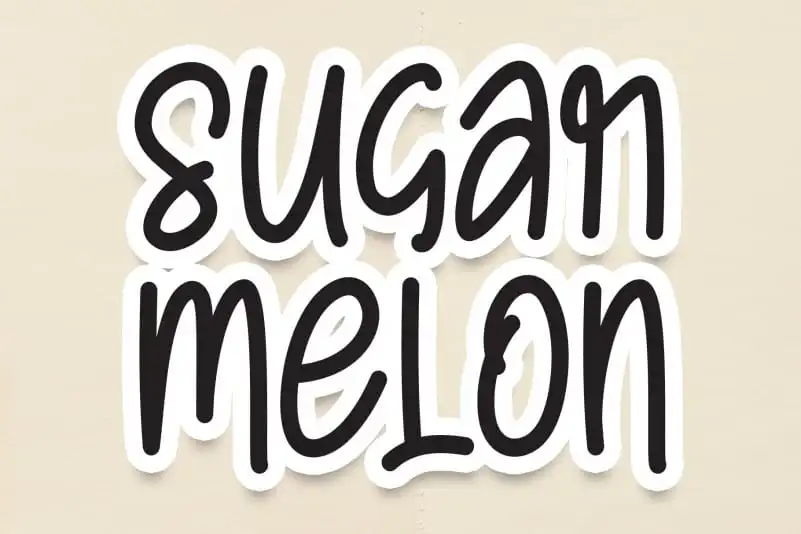
Sugar Melon Display Font – Download Grátis
A Sugar Melon Display Font é uma nova adição à coleção de caracteres digitais da creativeletter, apresentando-se como uma mistura única entre elegância e naturalidade. Este tipo de escrita é perfeito para designers que buscam um toque de criatividade na sua criação, trazendo profundidade e originalidade ao design. Embora seja classificado como um fonte de escrita feita à mão, a Sugar Melon Display Font não se limita apenas a esses limitados requisitos. Seu caráter fluido e expressivo permite que você explore uma variedade de estilos, desde letras delicadas até designs mais elaborados e chamativos. Este tipo é especialmente adequado para o uso em logotipos, selos, cabeçalhos ou qualquer outro elemento visual que deseje destacar sua personalidade e singularidade. Com um design cuidadosamente pensado, a Sugar Melon Display Font se torna uma fonte de escolha perfeita para aqueles profissionais que buscam adicionar emblemas únicos ao seu trabalho. Suas linhas curvas arredondadas e seus traços delicadamente contornados criam um visual envolvente, atraindo os olhos e proporcionando uma sensação de leveza e modernidade. Com sua rica textura e aparência sedosa, esta fonte de escrita feita à mão é perfeita para designers que querem dar vida aos seus projetos digitais, conferindo um toque especial e único. Seja você um estilista de moda, uma marca em constante evolução ou simplesmente alguém buscando desfrutar do poder transformador da linguagem visual, a Sugar Melon Display Font é o seu companheiro perfeito na jornada criativa.